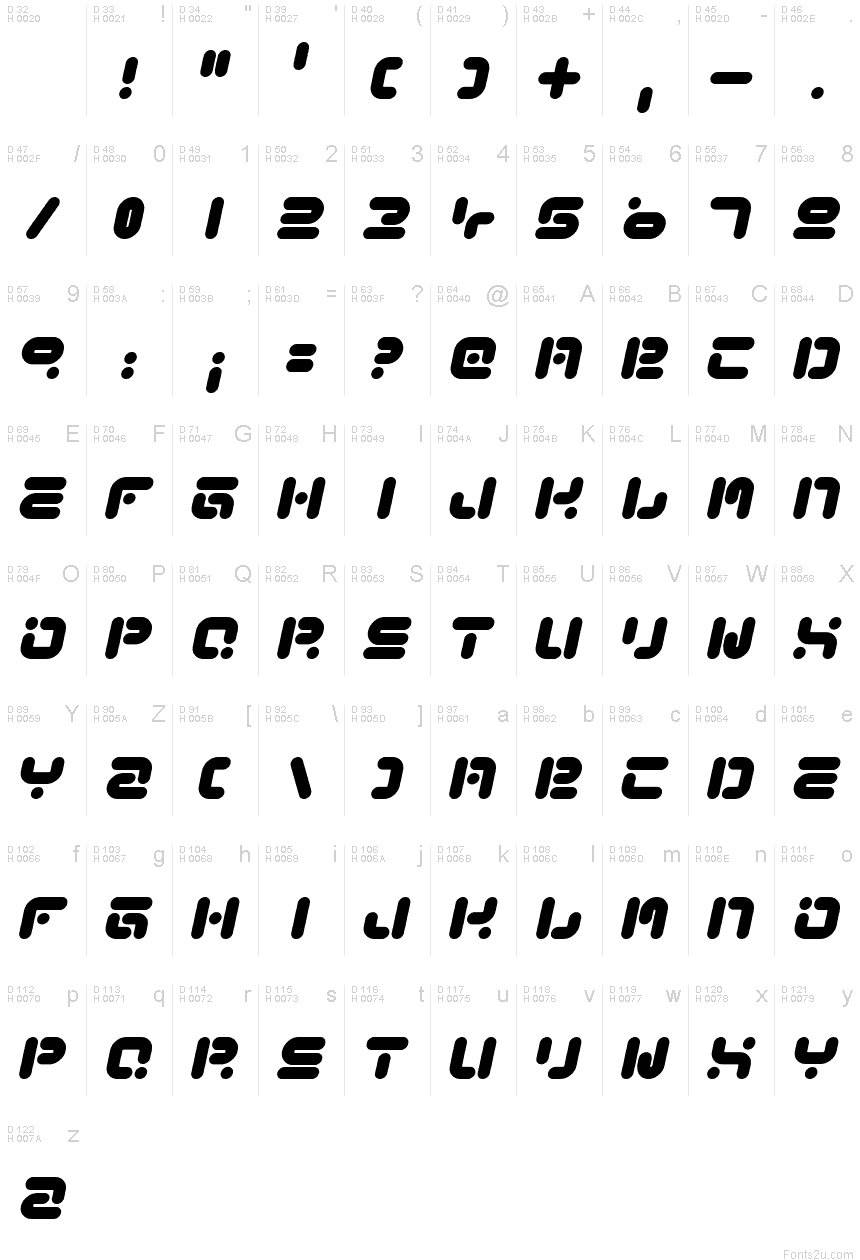
Funky Knut autorstwa Mr. Mieps to darmowy, futurystyczny krój typu display. Jej masywne, zaokrąglone pociągnięcia i gładkie łuki przypominają płynny plastik wylany na stronę, podczas gdy pochylenie do przodu nadaje każdemu słowu wrażenie ruchu. Rytm powtarzalnych pionowych form tworzy śmiały, niemal mechaniczny puls, ale miękkie krawędzie sprawiają, że całość pozostaje zabawna i przystępna, zamiast sprawiać wrażenie chłodnej.
Dzięki Funky Knut Twoje nagłówki natychmiast przenoszą odbiorcę w klimat sci-fi z późnych lat 90. – świetnie sprawdzi się na ulotkach rave, okładkach EDM, w technologicznym brandingu retro, logotypach gier, naklejkach i animacjach. Ten darmowy font najlepiej prezentuje się w dużych rozmiarach, gdzie jego soczyste kształty mogą w pełni wybrzmieć; połącz go z czystym, neutralnym krojem bezszeryfowym w tekście głównym, aby pozwolić Funky Knut nadać całości charakteru.